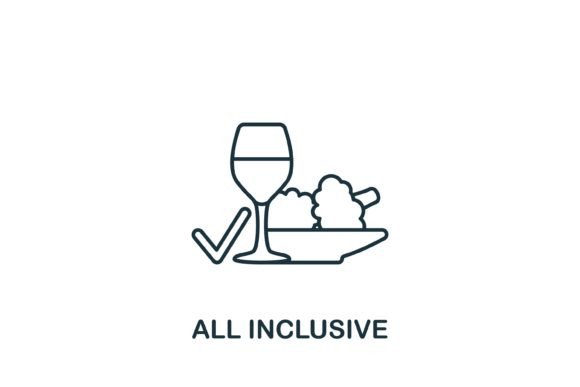
All Inclusive Icon
適切なデザイン要素を見つけるのは難しい場合がありますが、All Inclusive Iconは作品を即座に引き立てる優れたコレクションを提供します。
精密に作られたAll Inclusive Iconは、クリーンなベクター、滑らかなタイポグラフィ、そして安心のための商用ライセンスを提供します。
POD(オンデマンド印刷)製品、結婚式の招待状、またはソーシャルメディアのグラフィックを作成している場合でも、All Inclusive Iconは理想的です。